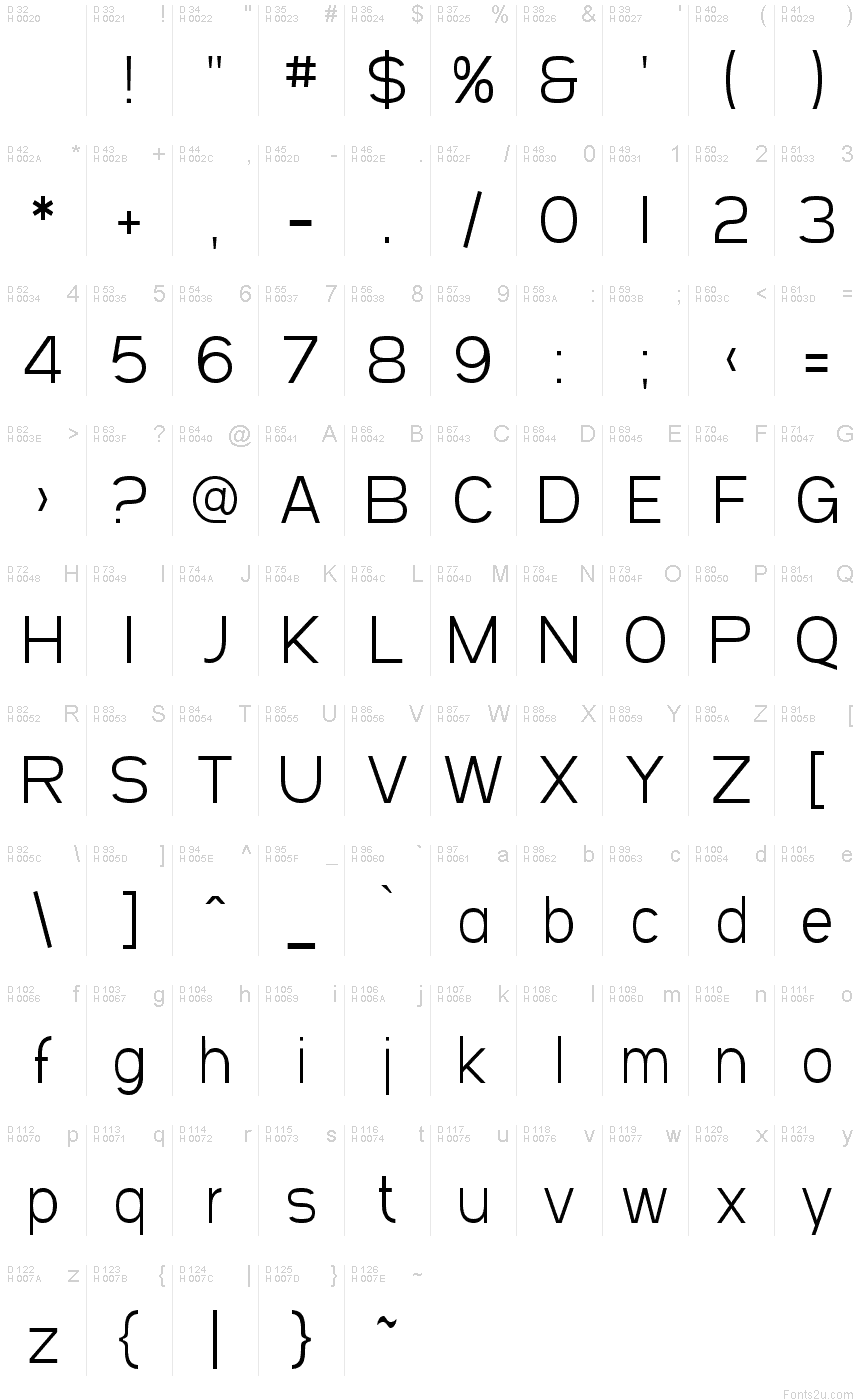
SF Arborcrest Light od ShyFoundry to darmowy, lekki krój bezszeryfowy o czystym, nowoczesnym charakterze. Litery zostały narysowane cienką linią o otwartych, przestronnych kształtach, dzięki czemu font sprawia wrażenie spokojnego i architektonicznego, a nie surowego.
Naturalnie pasuje do brandingu, plakatów galeryjnych, nagłówków w czasopismach, plansz tytułowych oraz minimalistycznych opakowań, gdzie odrobina światła wokół liter robi różnicę. Jako darmowy font, SF Arborcrest Light sprawdza się również w krótkich nagłówkach internetowych i na okładkach książek, zwłaszcza gdy szukasz subtelnego, wyważonego głosu zamiast czegoś topornego czy przesadnie geometrycznego.
SF Arborcrest Light
ShyFoundry
Derek Vogelpohl